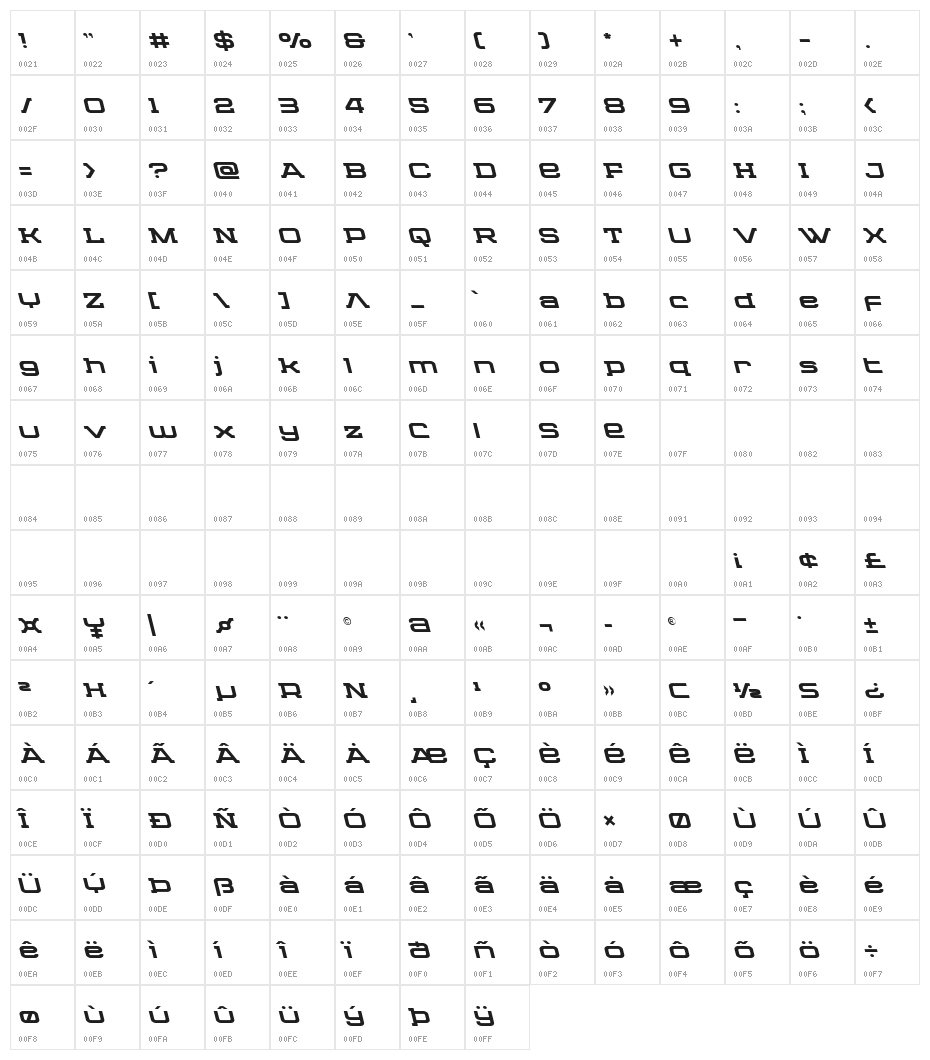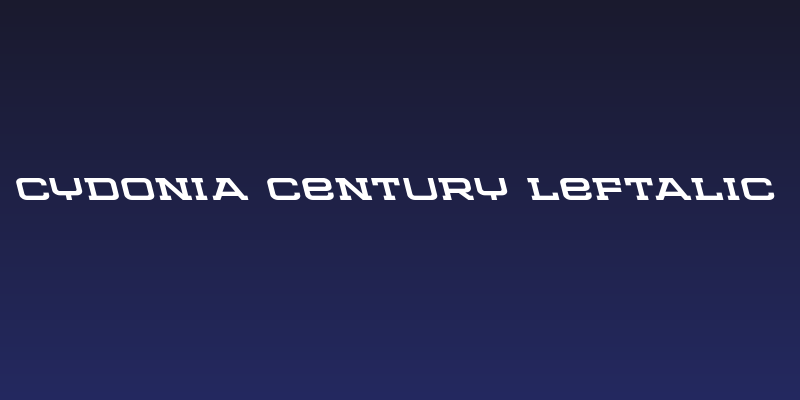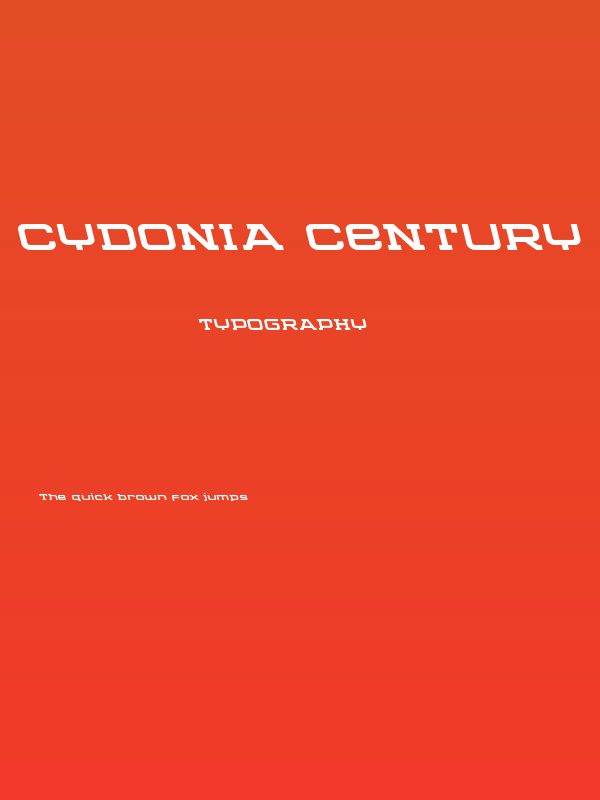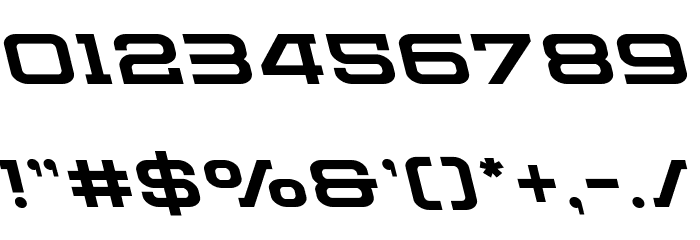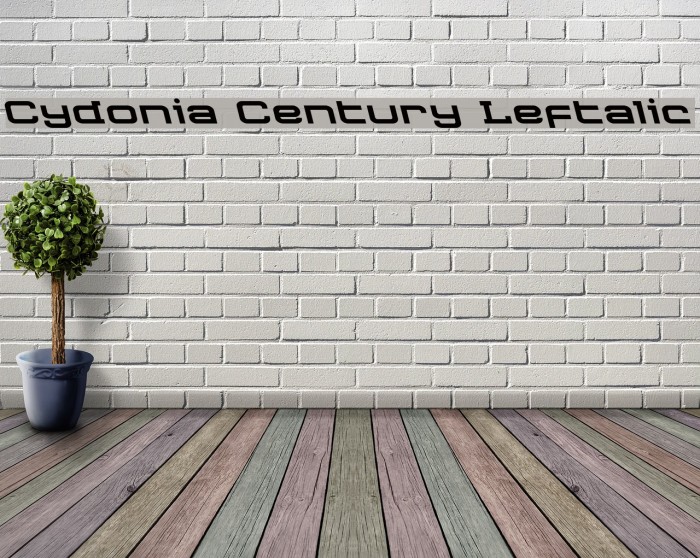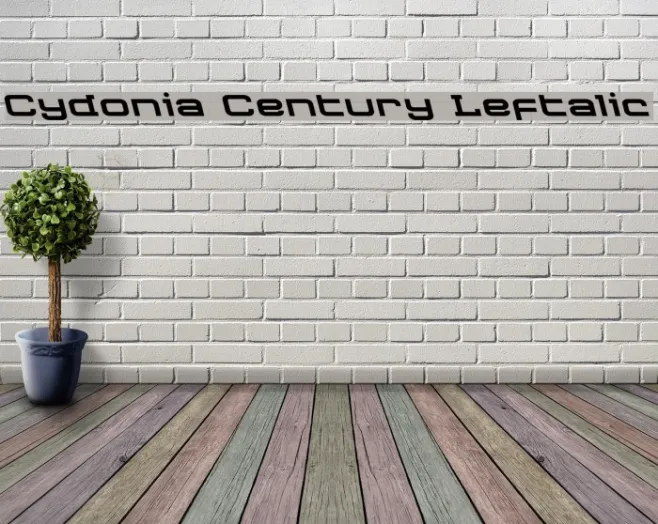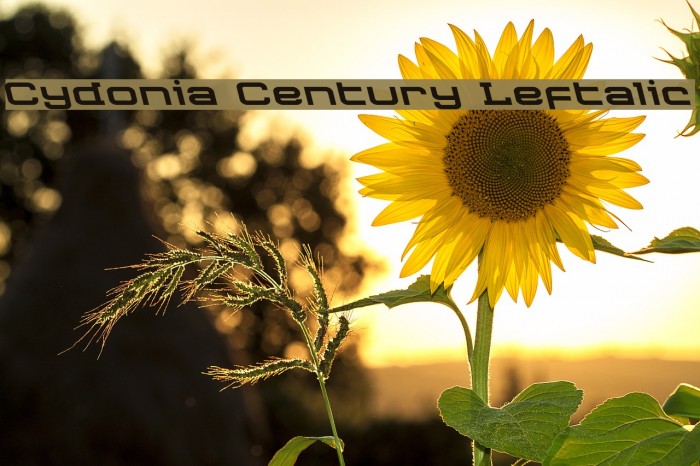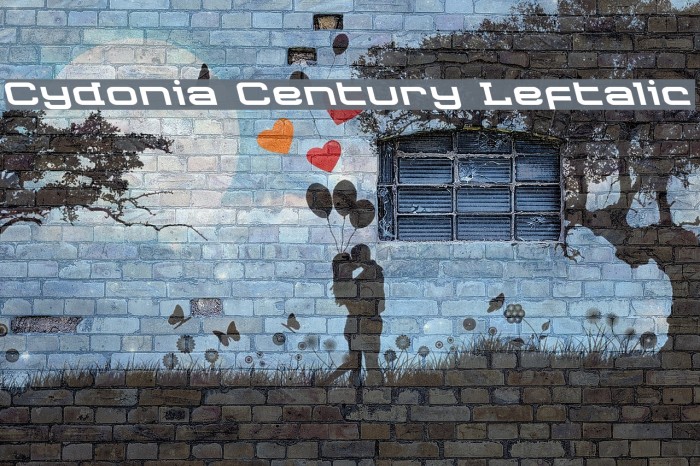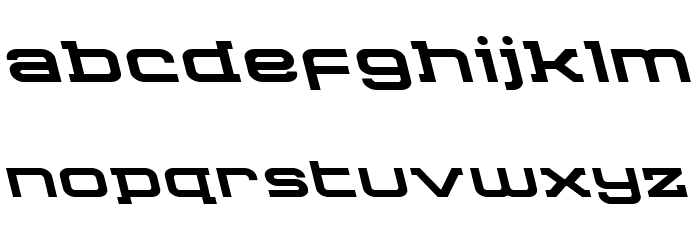
Cydonia Century Leftalic Font
| Proyectos propuestos | Ideal for technology branding, sci-fi themed projects, video game titles, and modern advertising campaigns. |